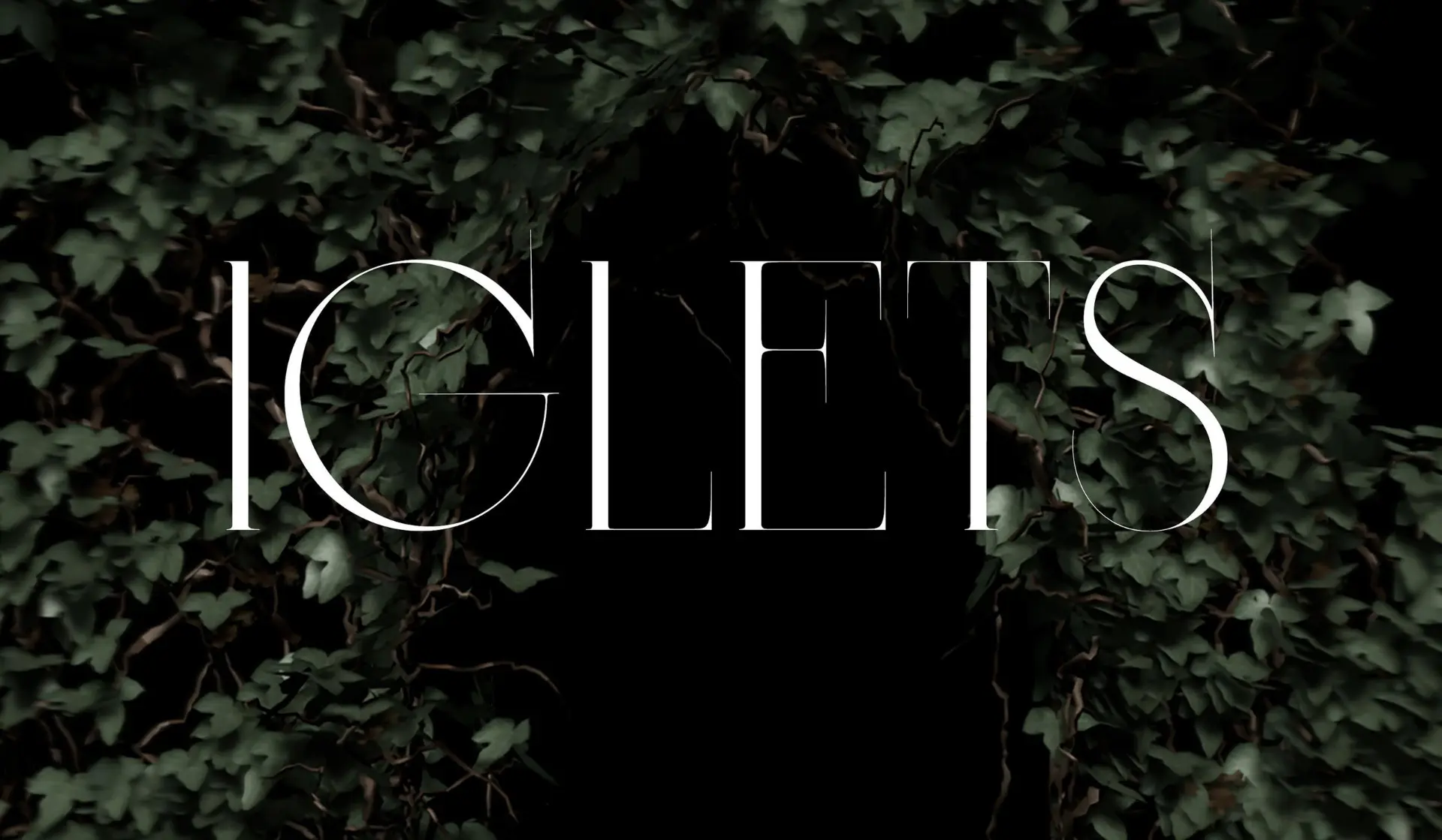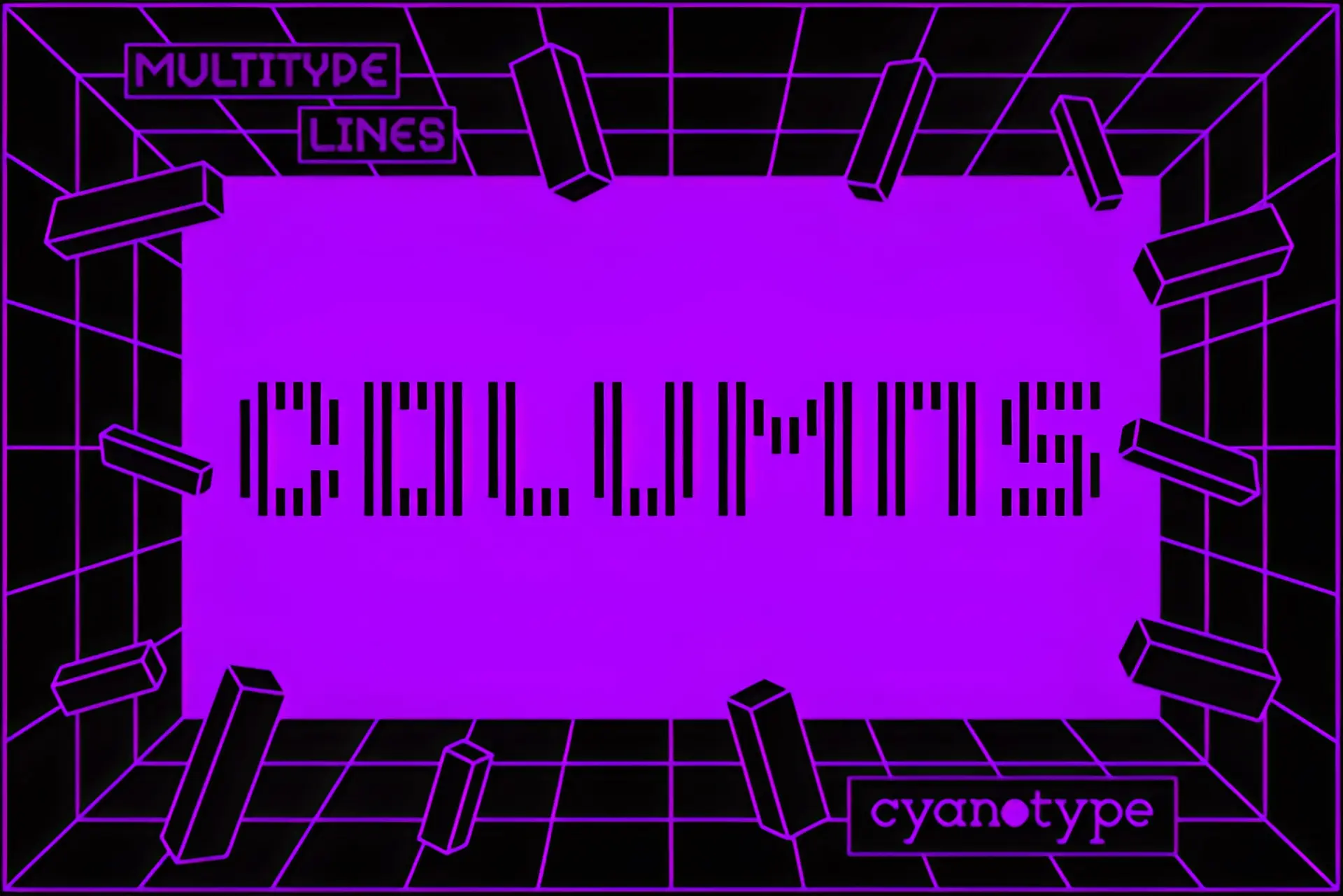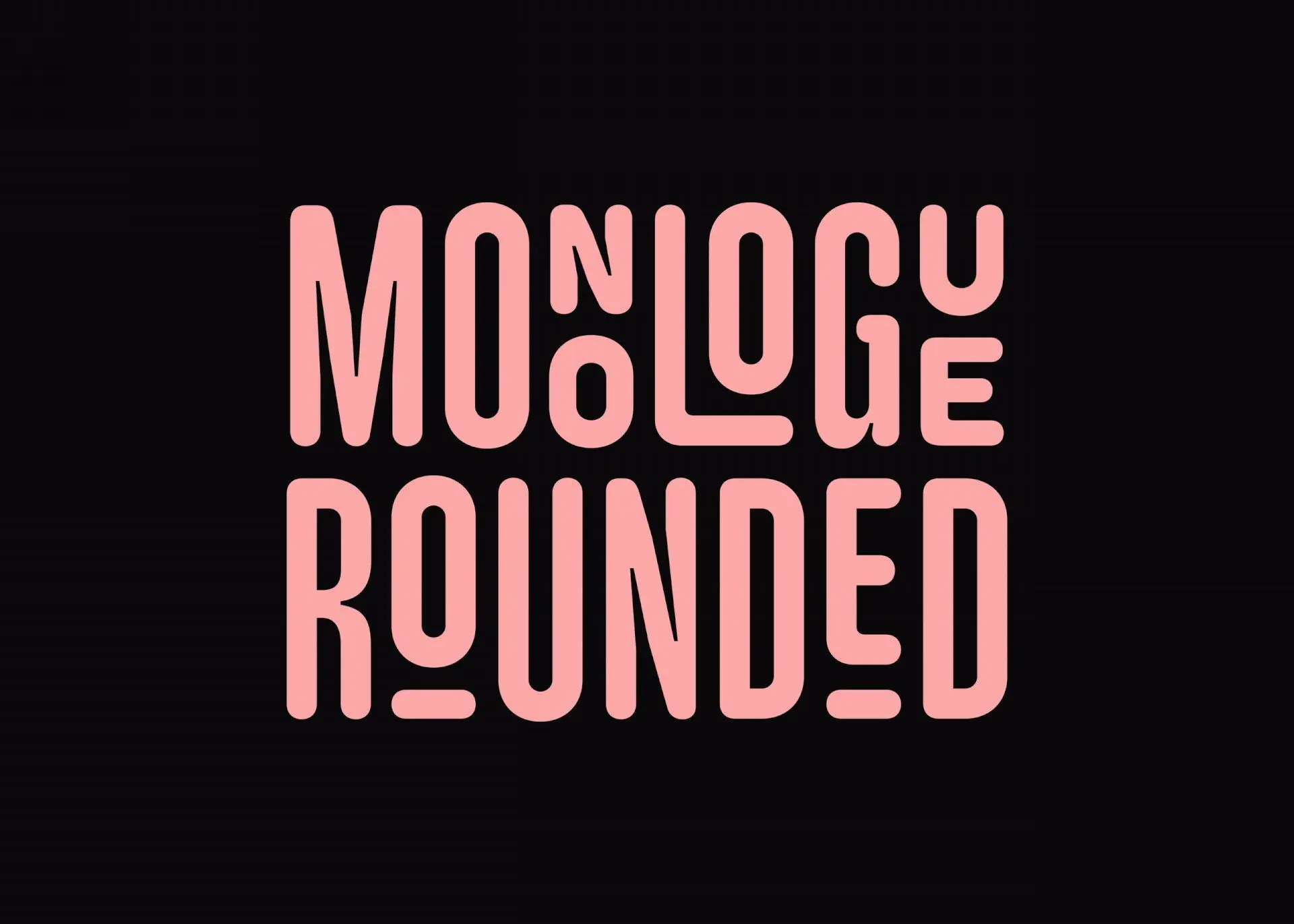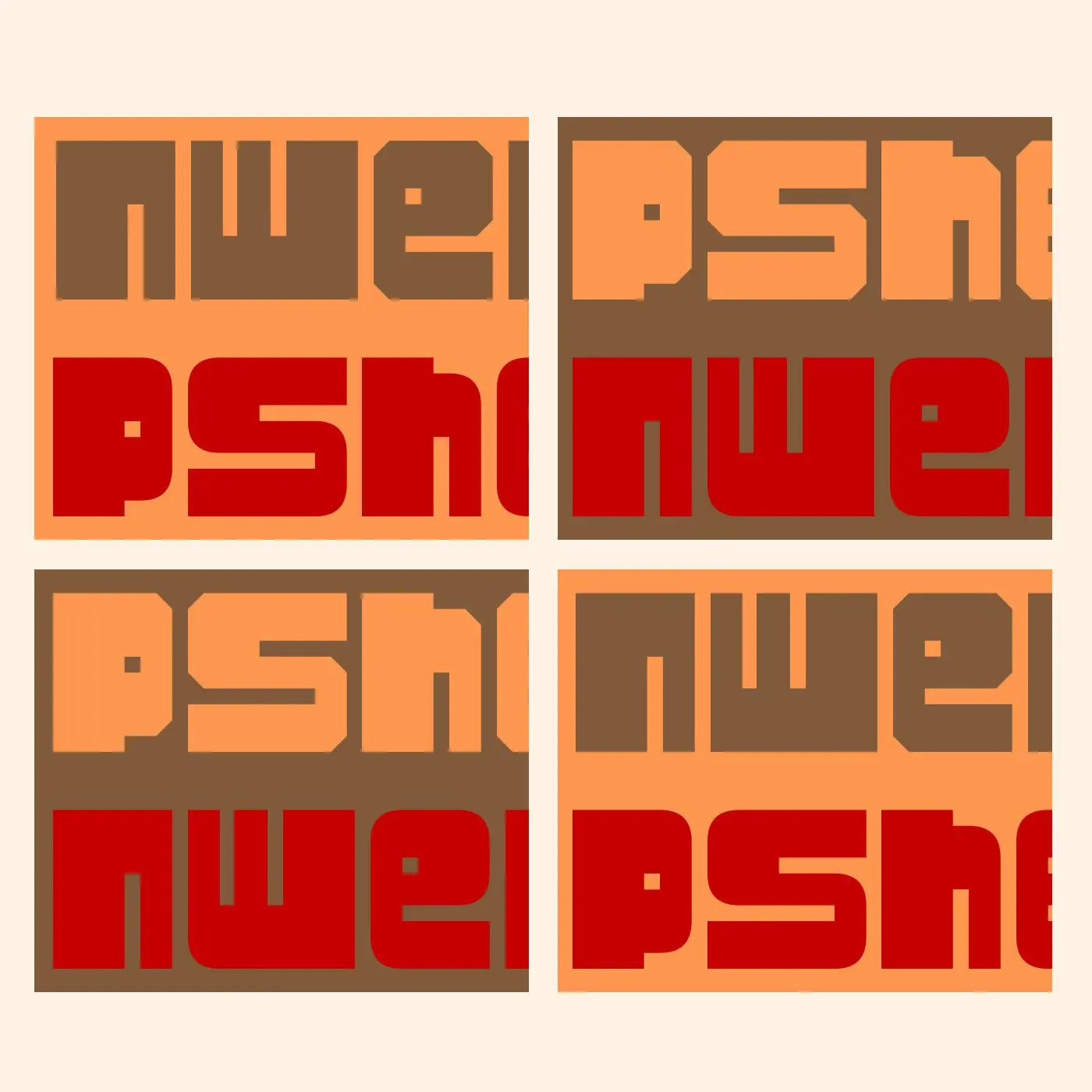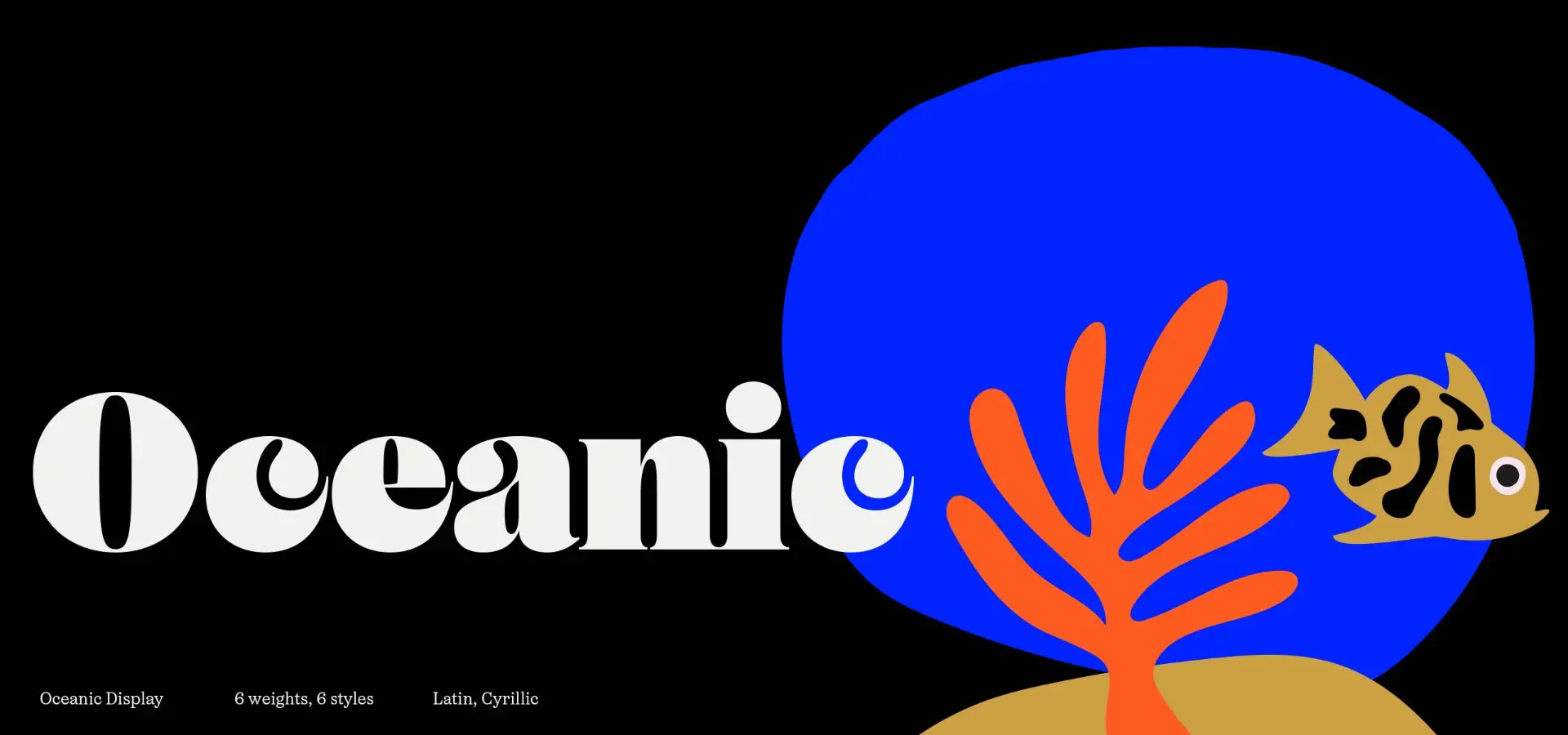
Шрифт Irch #Рукописные Симпатичный, тоненький, простой рукописный шрифт, бесплатный для личного и коммерческого использования. 🚩https://www.rufonts.ru/shrifty/shrift-irch/
Шрифт AA Lumos Caps как в Гарри Поттере #Декоративные Качественный кириллический шрифт по мотивам знаменитой истории о Гарри Поттере, который учился в Хогвартсе. В архиве 1 версия шрифта, содержащая в себе только заглавные символы, цифры 0-9, а так же большинство знаков препинания. Бесплатный шрифт для личного и коммерческого использования. 🚩 https://www.rufonts.ru/shrifty/shrift-aa-lumos-caps-kak-v-garri-pottere/
Шрифт Pshek #Декоративные Pshek — это универсальный шрифт без засечек в стиле 80-х, подходящий для заголовков и крупных надписей. Когда вы сталкиваетесь с острыми углами в своей жизни, всегда старайтесь сгладить их. 🚩 https://www.rufonts.ru/shrifty/shrift-pshek/
Шрифт Curely Typeface #Декоративные Красивый, кудрявый декоративный шрифт. В архиве 1 начертание. 🚩https://www.rufonts.ru/shrifty/shrift-curely-typeface/
Шрифт Wizland #Рукописные Магический рукописный бесплатный шрифт. В архиве одно начертание. 🚩 https://www.rufonts.ru/shrifty/shrift-wizland/
Шрифт ST-Simple Square #Гротеск Бесплатный крупный гротескный, космический шрифт. Подойдет для оформления заголовков, статей, журнальных обложек и прочего. 🚩 https://www.rufonts.ru/shrifty/shrift-st-simple-square/
Шрифт Robtronika #Гротеск Абсолютно бесплатный гротеск с закругленными углами. Используйте в любых целях. 🚩https://www.rufonts.ru/shrifty/shrift-robtronika/
Шрифт Iglets #Антиква Эстетичный шрифт в стиле антиква студента 3 курса Школы Дизайна НИУ ВШЭ в Петербурге. Распространяется бесплатно. 🚩 https://www.rufonts.ru/shrifty/shrift-iglets/
Шрифт Monologue Rounded #Гротеск Доработка предыдущей версии гротескного шрифта Monologue, — теперь шрифт приобрел закругленные углы. Триал версия для тестирования перед покупкой. Купить шрифт можно перейдя по имени автора на сайте. 🚩 https://www.rufonts.ru/shrifty/shrift-monologue-rounded/
Шрифт Volshebstvo TD #Декоративные Стильное решение для акцентов и небольших заголовков с выразительным декоративным стилем и поддержкой кириллицы, доступен бесплатно для личного и коммерческого применения и станет идеальным выбором для проектов с фэнтезийной или старинной тематикой. 🚩 https://www.rufonts.ru/shrifty/shrift-volshebstvo-td/
Шрифт Dela Gothic One #Гротеск Мощный, широкий гротеск с качественной прорисовкой всех символов. Полностью бесплатный. 🚩🚩https://www.rufonts.ru/shrifty/dela-gothic-one/
Шрифт MultiType Lines Columns #Декоративные Декоративный гротескный шрифт создан из вертикальных полос. Распространяется полностью бесплатно. 🚩 https://www.rufonts.ru/shrifty/multitype-lines-columns/
Шрифт Oceanic #Антиква Красивый, крупный и изящный шрифт в стиле антиква. В архиве триал версия 6 гарнитур. Бесплатный для личного использования. За полной версией и для коммерческого использования кликайте на имя автора на сайте. 🚩 https://www.rufonts.ru/shrifty/shrift-oceanic/